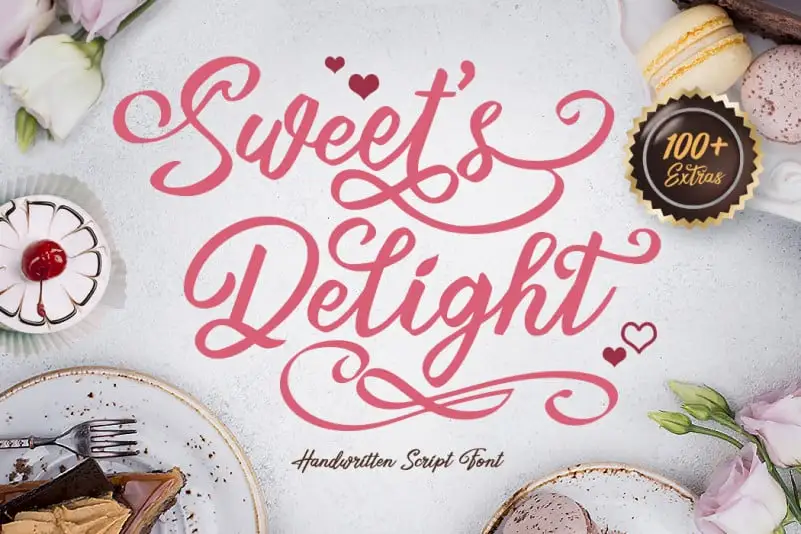
Sweet’s Delight Script Font – Fonte Grátis
Sweet's Delight Script Font
A Sweet’s Delight Script Font é uma elegante tipografia cursiva que se destaca pela sua forma suave e fluidez natural. Esta fonte dá seu próprio toque único a cada palavra, criando um ar de felicidade, conforto, entusiasmo e amor. Perfeita para cabeçalhos em todo tamanho, decoração de bolo, convites, web ou todos os tipos de produtos impressos e objetos artesanais, logotipos e marcas, posts nas redes sociais, anúncios e designs de produtos, entre outros usos. Com mais de 72 swashes e 62 gráficos (incluindo plantas, babados, corpinhos, taças de chá e biscoitos), a Sweet’s Delight Script Font oferece um vasto leque de personalização para seus projetos. Adquira agora e desfrute dos detalhes que irão tornar seu trabalho ainda mais único e profissional.